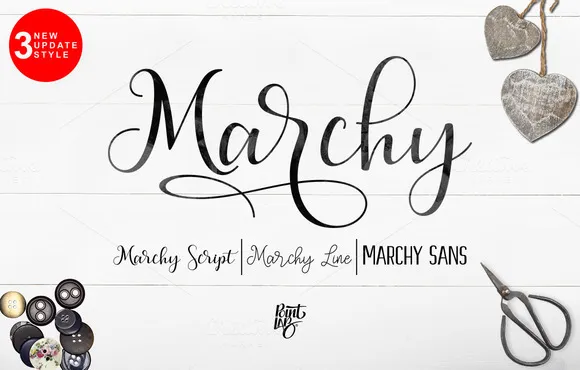
Marchy Script Font – Download Grátis
A Fonte ‘Marchy Script’ é uma inovação na categoria dos fonts script, apresentando um estilo fresco e moderno com um toque delicado de calligrafia. Com caracteres decorativos que se movem e dançam no papel, esta fonte traz a elegância única do calligrafismo para diversos projetos digitais. Seja para invitations, cartas de cumprimentos, materiais de marca, cartões de visita ou até mesmo painéis publicitários – ‘Marchy Script’ enfeita seus designs com um toque sofisticado e autêntico. Perfecta para quem busca uma fonte versátil que se adapta a diversos usos e propósitos.